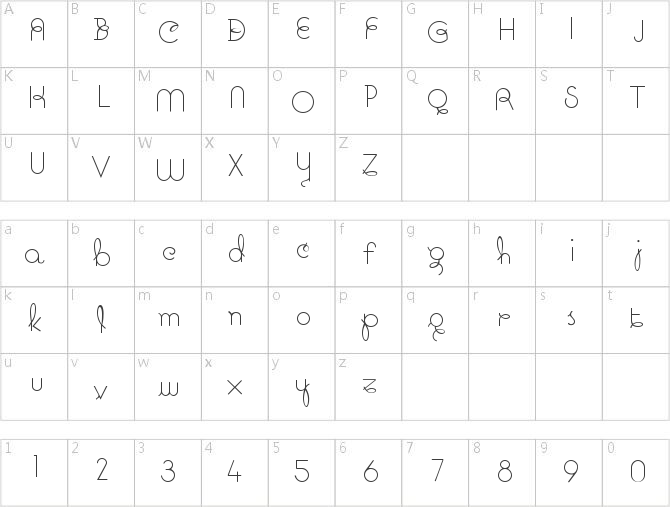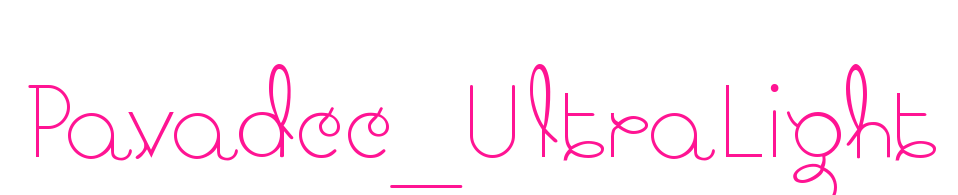
字體名稱: Pavadee
Pavadee_UltraLight
Pavadee_UltraLight字體字庫是一款讓人賞心悅目、百看不厭的英文字體,適合各類廣告和產(chǎn)品包裝設(shè)計(jì)應(yīng)用,字體大小0.17MB,格式為ttf字體,上傳用戶是晴朗,作者/版權(quán)方為未知